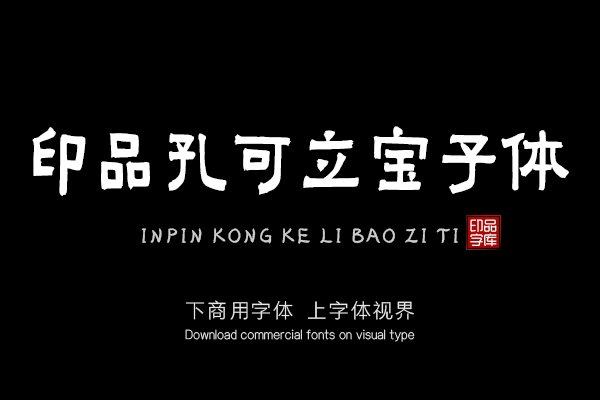
字库名字:印品孔可立宝子体
字库制作:印品字库
字库作者:孔可立(是由孔子第74代孙”孔可立“老先生亲笔所写)
1、字体设计灵感:
一,字体創作灵感。中国汉字是人类文明的活化石,在数千年历史中承传应用焕发着不朽的生命力。是字体創作取之不尽用之不竭的源泉。
二,字体简介。爨宝子碑刻于东晋四年(公元405年)的云南边陲。是汉代隶书渐变为楷书的唯一存世而方笔用笔古朴奇拙的优秀书法艺术作品!后世师法者驱之若骛。
三,孔可立宝子体是孔可立先生积五十年爨宝子碑临池心得,辅以张迁碑,爨龙颜碑,嵩髙灵庙碑等笔意而卓然形成个性鲜明的纯方笔楷书,具备典型的艺术生命力!